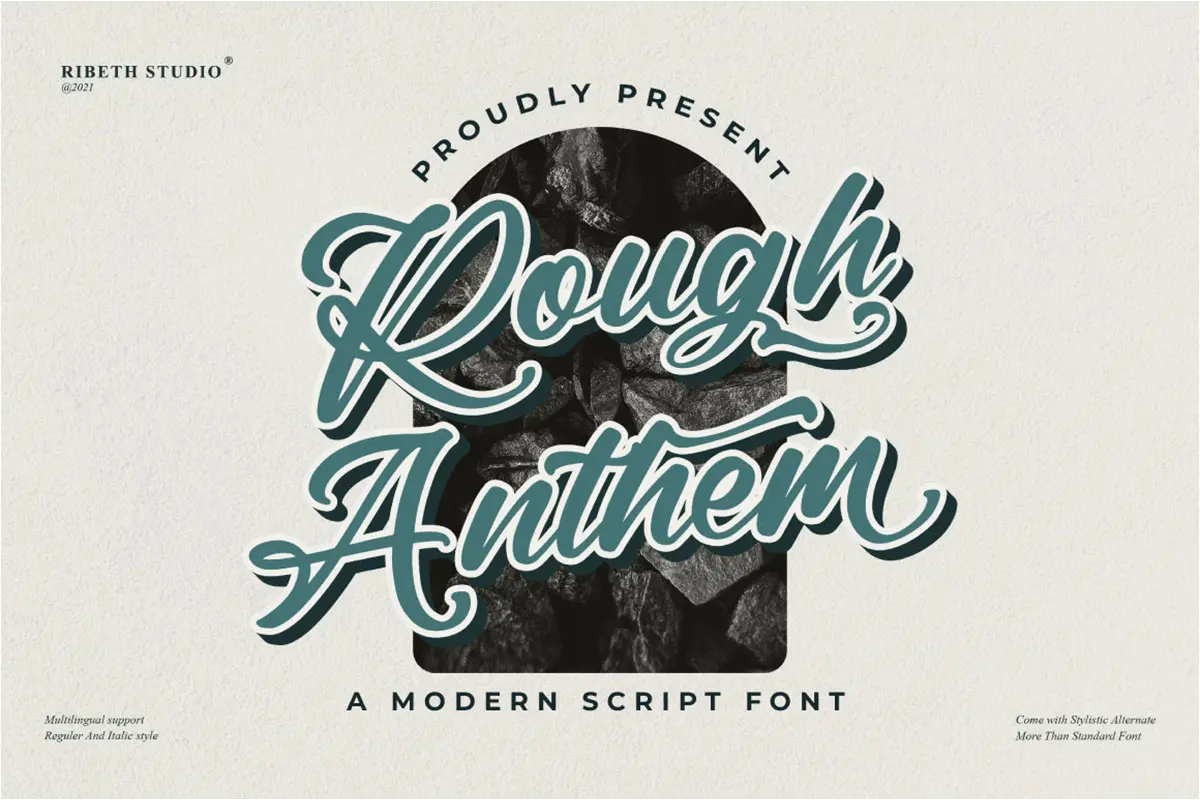
فونت دستنویس مدرن و حرفهای
فونت دستنویس مدرن و شیک با دو سبک مختلف، مناسب طراحی لوگو، برندینگ، بستهبندی محصولات، کارت دعوت، نقلقولهای گرافیکی، پوستر و طراحی پوشاک.
این فونت دستنویس مدرن با طراحی زیبا و حرفهای، انتخابی فوقالعاده برای طراحانی است که به دنبال ایجاد ظاهری خاص، خلاقانه و چشمنواز در پروژههای خود هستند. سبک روان و طبیعی حروف در کنار جزئیات دقیق طراحی، باعث شده این فونت برای انواع پروژههای گرافیکی و تبلیغاتی کاربرد گستردهای داشته باشد.
این مجموعه شامل دو سبک مختلف معمولی و ایتالیک بوده و علاوه بر حروف بزرگ و کوچک انگلیسی، از اعداد، علائم نگارشی، کاراکترهای چندزبانه، لیگچرها، حروف جایگزین و کشیدگیهای تزئینی نیز پشتیبانی میکند. وجود این امکانات باعث میشود بتوانید ترکیبهای متنوع و حرفهای برای طراحی لوگو، برندینگ و آثار تبلیغاتی ایجاد کنید.
این فونت برای طراحی هویت بصری برند، لوگو، بستهبندی محصولات، کارت دعوت، برچسب کالا، پوسترهای تبلیغاتی، چاپ روی پوشاک، شبکههای اجتماعی و بسیاری از پروژههای گرافیکی دیگر گزینهای ایدهآل محسوب میشود.
ویژگیهای محصول:
- طراحی دستنویس مدرن و حرفهای
- شامل دو سبک معمولی و ایتالیک
- پشتیبانی از کاراکترهای چندزبانه
- دارای لیگچرهای حرفهای
- شامل حروف جایگزین
- دارای کشیدگیهای تزئینی
- پشتیبانی از PUA
- مناسب طراحی لوگو و برندینگ
- دارای سبک معمولی (Regular)
- دارای سبک ایتالیک (Italic)
- پشتیبانی از کاراکترهای چندزبانه
- شامل Ligatures، Alternates و Swash
کاربردها:
- طراحی لوگو
- طراحی هویت بصری برند
- بستهبندی محصولات
- کارت دعوت و مراسم
- طراحی پوستر
- طراحی برچسب محصولات
- چاپ روی تیشرت و پوشاک
- طراحی نقلقولهای گرافیکی
- تولید محتوای شبکههای اجتماعی